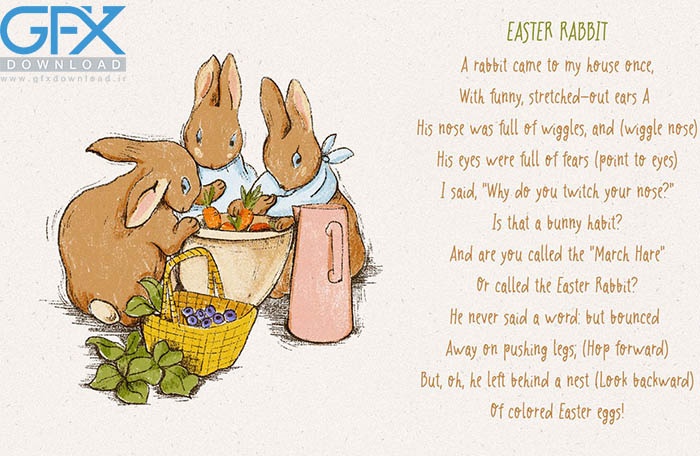
دانلود فونت هویج Red Carrot
فونت هویج و سرگرم کننده Red Carrot
دانلود فونت هویج و سرگرم کننده Red Carrot
در این پست با معرفی فونت انگلیسی جدید دست نویس قرمز هویج با فرمت WOFF با ما همراه باشید. دانلود فونت هویج Red Carrot برای هر پروژه برندسازی مانند لوگو، چاپ تی شرت، esport و بسیاری موارد دیگر مناسب است.